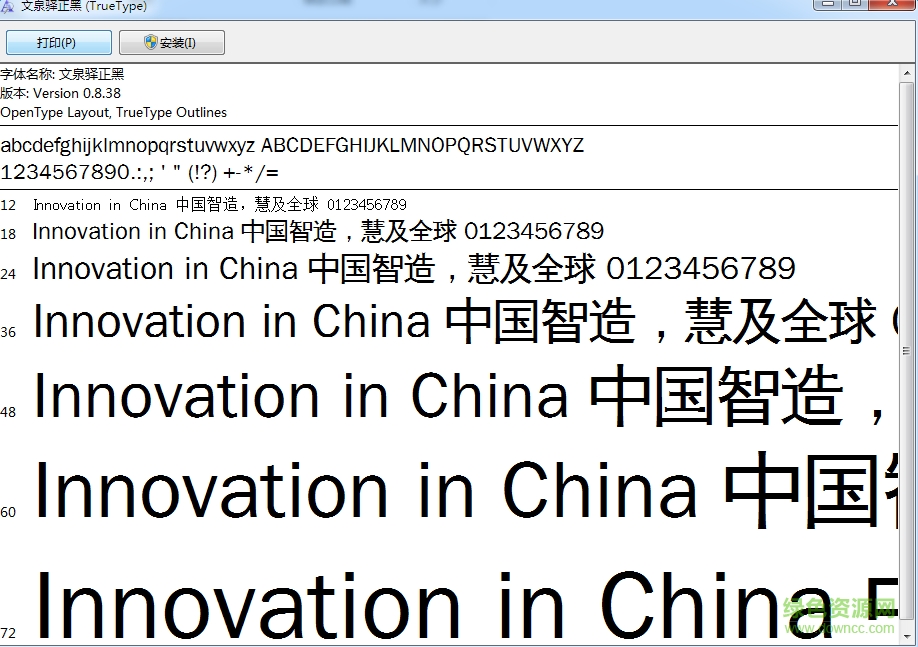
文泉驛正黑字體是一款非常有特色的電腦黑體字體,整體筆畫(huà)看起來(lái)清晰,易于閱讀,適用范圍廣泛。從設(shè)計(jì)到制作再到審稿及全部字形的校對(duì)每一個(gè)環(huán)節(jié)都精心完成,確保字庫(kù)質(zhì)量的精良,喜歡可以來(lái)綠色資源網(wǎng)下載體驗(yàn)!
文泉驛正黑,一種支持大字符集的開(kāi)源字體,可用于正文、小標(biāo)題、大標(biāo)題、海報(bào)、大型牌匾及屏顯用字。整個(gè)系列風(fēng)格完全一致,不管是常用字或是非常用字,字字精美、結(jié)構(gòu)端正、重心平穩(wěn)、美觀(guān)實(shí)用。